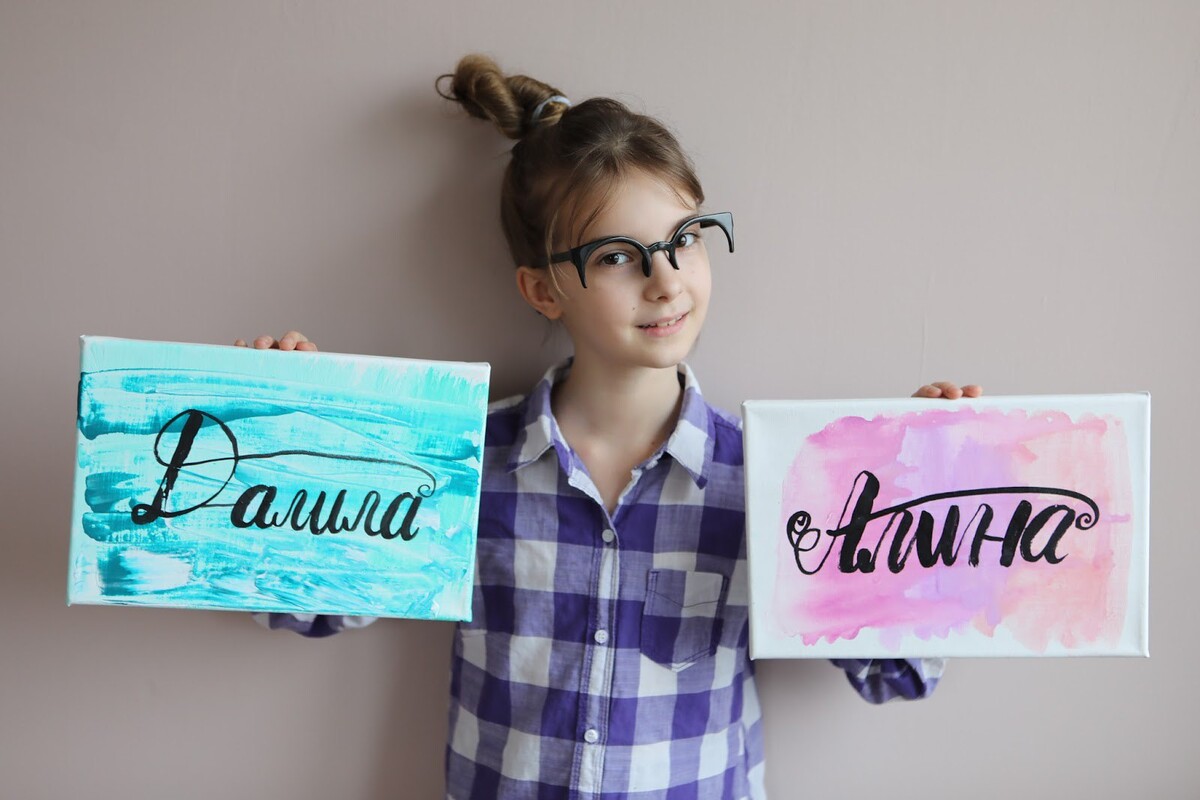
Славяне было почти 8 лет и она совершенно не любила писать.
Меня это не смущало, т.к. мы на самообразовании и нет необходимости сдавать аттестации в определенный период, а значит мы можем дождаться момента, когда желание приобрести навык письма появится само.
Всему свое время.
Но все же, периодически я ее подталкивала к использованию письма в жизни. Она писала записочки мне, письма зубной фее, ставила подписи на своих картинах, писала исследования о животных.
Однажды ей пришлось испытать на собственном опыте необходимость быстрого письма
Мы учились на курсе русского языка в школе Романовой и в течение 10 дней писали веселые слова и фразы, изучая фонетику. Этот курс был не совсем по возрасту. Своего рода эксперимент, который дал хорошие результаты. Уроки веселые и вполне понятные, но скорость письма и объем ОООООЧЕНЬ сложен для нее! Про почерк тогда говорить было бессмысленно, справлялась как могла, по три слова на странице огромными печатными буквами.
После курса мы стали практиковать полученные знания по русскому и, в том числе, письменные практики делать. Я попыталась дать ей прописи, чтобы постепенно переходить с гигантомании на уменьшение и с печатных букв на прописные. Поехали в книжный, она сама долго выбирала школьные прописи, купила парочку. Но по сей день они лежат практически не использованные. И особого энтузиазма в занятиях не было. Выводить буковки не просто сложно! Это ужасно скучно! Особенно если не понимаешь зачем.
И какой тут смысл для ребенка?
Я понимала, что она не видит его и значит нет ни желания, ни мотивации делать бессмысленное дело. Разговоры про красивый почерк не убедили ее.
Честно говоря, они и меня не убеждали, потому что тема почерка вообще очень странная - сейчас мы не пишем письма вручную (а жаль), документы заполняем печатными, даже в школе дети экзаменационные дисциплины пишут печатными. Время настолько изменилось, что простому человеку его (почерк) негде использовать.
Зачем красиво писать?
Точнее - зачем иметь красивый почерк?
И тратить на это так много сил и времени.
Было совершенно очевидно, что школьный метод - ежедневно, монотонно отписывать буковки в прописях - абсолютно неэффективен в нашем подходе. Будет идти через усилие и принуждение, а значит без удовольствия, энтузиазма и радости. А знааачит.... нам не подходит.
Я озадачилась: как заинтересовать ребёнка?
Есть ли другой подход, кроме стандартного "садись ровно и пиши прописи"?
Головой я понимала, чтобы научиться писать красиво, нужны регулярные тренировки, кропотливая работа, концентрация, терпение, усидчивость. Без качественной мотивации и любви к этому делу ничего не выйдет. Поэтому именно с любви мы и начали. И с поиска смысла!
В чем смысл письма? Я задавала этот вопрос себе. И не находила ответа. Точнее с позиции взрослого тут все понятно. А для ребенка? Зачем?
Чтобы делать задания в школе?
Потому, что надо уметь писать? Все учатся этому?
Поверьте, для ребенка все это не важно. Эти смыслы им не интересны, не впечатляют.
“Я тоже так хочу научиться!”
— сказала Славяна, когда увидела работы современных каллиграфов. Одни выводили очень красивые буквы тонким пером на свадебных открытках, писали мелом на стенах, кистью на огромных холстах, другие оформляли стены авторскими надписями, одежду принтами, блокноты, посуду, расписывали интерьеры и даже целые здания. Каждый день мы находили что-то новое и дети удивлялись, что это тоже письмо.
И это был шаг №1 - увидеть смысл.
С этого момента началась практическая часть занятий — дети стали осваивать разные техники письма. Начали с кисти и туши, постепенно переходили на тонкое перо, с больших форматов на маленькие.
Все через игру и творчество: рассматривали и обсуждали различные шрифты, создавали свои собственные, тестировали разнообразные инструменты и материалы. Задания я придумывала сама и адаптировала для них из взрослых курсов.
Девочки в процессе делали собственные открытия:
- плакатные перья и остроконечные дают совершенно разный вариант написания одной и той же буквы,
-вариантов начертания букв может быть великое множество,
- изображение буквы может выражать настроение,
- в одном шрифте у каждой буквы есть общие стилизованные элементы,
- упаковка шоколада и всего, что есть в магазинах придумана не просто так, а со смыслом,
- надписи на дорогих и дешевых продуктах совершенно разные, чтобы задуманная надпись уместилась, надо посчитать количество букв и для каждой определить свое место
и многое другое.
Самое мое любимое открытие случилось на второй день после того, как мы ввели в дополнение к прописным практикам устные игры.
Славяна заявила: “Мама, весь мир состоит из букв!”
Это был шаг №2 - практика через игры и активация интереса в буквам
Буквы стали нужны, буквы стали важны!
Интерес детей активно поддерживался моим интересом.
Это важно — погрузиться в тему вместе с детьми. По-честному и с удовольствием искать, изучать, делиться с ними и направлять.
"Я тебя люблю, дорогая МАМА!", - написано на листе.
Сегодня ей 6 лет и прогресс на лицо! Мы не тренировались специально, только играли в буквы. В каждом задании игре для Славяны был вариант и для Султаны и так, она выучила все буквы, научилась ровно писать без разлиновки и даже читать.
Так, мы увидели, что игра в каллиграфию подходит всем детям, вне зависимости от возраста.
Если говорить о регулярном письме, то мы в курсе используем как основу кисть и рукописный шрифт кистью и именно ею и пишем. Это легче и интереснее детям. И так же пробуем другие инструменты